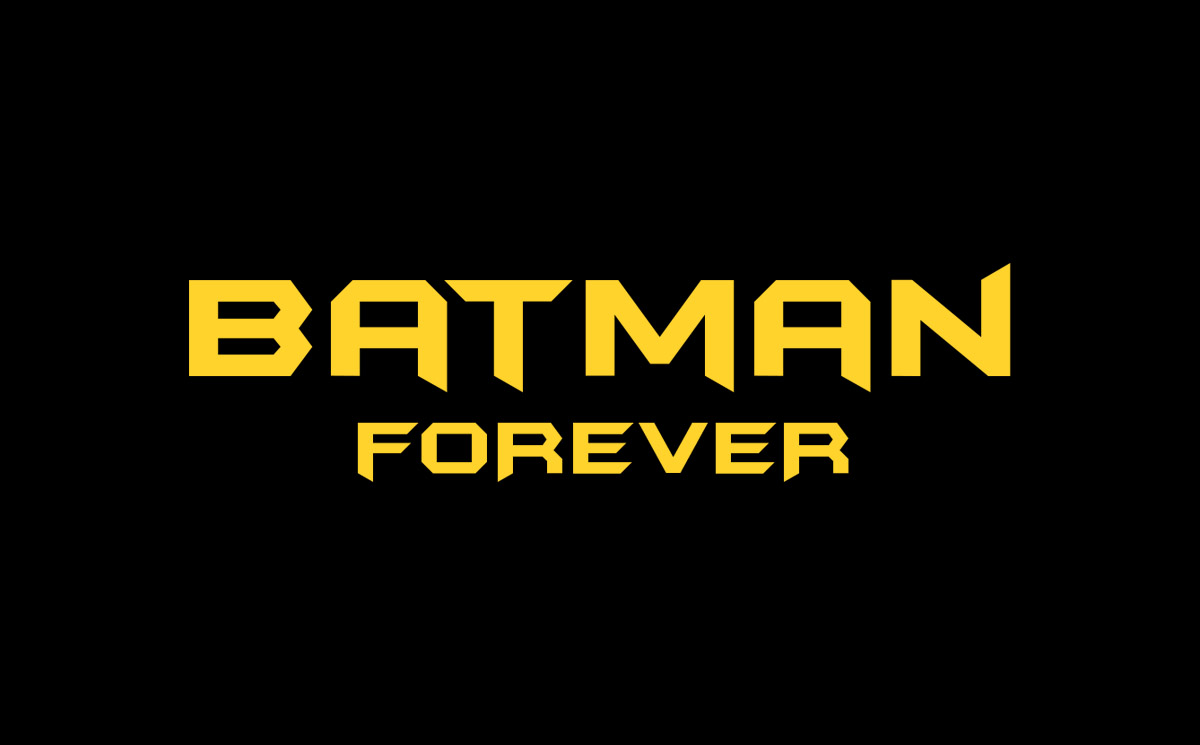
Nếu bạn đang tìm kiếm một bộ phông chữ mang phong cách mạnh mẽ, bứt phá và tràn đầy năng lượng cho các dự án sáng tạo, thì font thể thao cứng cáp Việt hóa SVN Batman chính là sự lựa chọn hoàn hảo không thể bỏ qua. Với cấu trúc nét chữ dày dặn, các góc vát dứt khoát cùng tinh thần hiện đại, bộ font này giúp truyền tải trọn vẹn sự quyết đoán và bản lĩnh trong từng thông điệp. Sự xuất hiện của bản Việt hóa chuẩn xác giúp các nhà thiết kế dễ dàng ứng dụng vào các sản phẩm đồ họa tiếng Việt mà không gặp bất kỳ trở ngại nào về mặt kỹ thuật.
Font Thể Thao Cứng Cáp Việt Hóa SVN Batman – Giải Pháp Typography Đột Phá Cho Thiết Kế Hiện Đại
Trong thế giới thiết kế đồ họa thương mại, typography đóng vai trò như chiếc chìa khóa định hình cảm xúc và truyền tải thông điệp cốt lõi của thương hiệu. Font thể thao cứng cáp Việt hóa SVN Batman nổi lên như một giải pháp thiết kế ấn tượng nhờ sự kết hợp hài hòa giữa hình khối hình học hiện đại và tinh thần thể thao cuồng nhiệt. Bộ font này không chỉ mang đến diện mạo mới mẻ cho các ấn phẩm quảng cáo mà còn khẳng định tính chuyên nghiệp trong từng chi tiết nhỏ nhất. Dù bạn đang thực hiện dự án truyền thông cho một giải đấu bóng đá lớn, thiết kế áo thi đấu cho đội tuyển esports hay xây dựng bộ nhận diện cho thương hiệu gym và fitness, SVN Batman đều có khả năng đáp ứng xuất sắc mọi yêu cầu khắt khe về thẩm mỹ lẫn công năng thị giác.
Phong cách thiết kế góc cạnh, đậm chất thể thao và tràn đầy uy lực
Font thể thao cứng cáp Việt hóa SVN Batman sở hữu những đường nét thẳng dứt khoát kết hợp cùng các góc vát tỉ mỉ, tạo nên cảm giác kiên cố và vô cùng hiện đại. Bộ chữ được xây dựng dựa trên tỷ lệ hình khối chuẩn xác, tạo ra sự cân bằng hoàn hảo giữa chiều rộng và chiều cao của từng ký tự. Nét chữ dày và đậm giúp các dòng tiêu đề (headline) luôn nổi bật, thu hút sự chú ý của người xem ngay từ cái nhìn đầu tiên. Tinh thần của font chữ này truyền tải sự quyết đoán, sức mạnh vượt trội và khát khao chiến thắng – những yếu tố vô cùng quan trọng đối với ngành công nghiệp thể thao và giải trí năng động.
Hỗ trợ Việt hóa toàn diện, chuẩn xác từng ký tự dấu tiếng Việt
Một trong những điểm cộng lớn nhất của font chữ này chính là phiên bản Việt hóa SVN được thực hiện một cách chỉn chu và tỉ mỉ. Các dấu thanh trong tiếng Việt như sắc, huyền, hỏi, ngã, nặng cùng các dấu phụ cho chữ cái ê, ô, ơ, ư, đ đã được thiết kế lại khéo léo để giữ nguyên tỉ lệ và phong cách góc cạnh của bộ chữ gốc. Nhờ đó, các bản thiết kế tiếng Việt của bạn sẽ không gặp phải tình trạng bị lỗi font, mất dấu hay các dấu thanh bị đè lên nét chữ. Việc hỗ trợ đầy đủ bộ gõ Unicode chuẩn giúp bạn dễ dàng soạn thảo văn bản trên mọi phần mềm mà vẫn đảm bảo tính thống nhất và tính thẩm mỹ cao nhất.
Tối ưu hóa cho thiết kế áo đấu, ấn phẩm Esports và Logo thương hiệu
Với đặc trưng nét chữ cứng cáp và vững chãi, SVN Batman đặc biệt phù hợp để ứng dụng trong thiết kế số áo và tên cầu thủ trên các bộ trang phục thi đấu như bóng đá, bóng rổ, bóng chuyền hay marathon. Nét chữ rõ ràng giúp khán giả dễ dàng nhận diện từ khoảng cách xa, đồng thời tạo nên vẻ ngoài ấn tượng và chuyên nghiệp cho đội hình thi đấu. Bên cạnh đó, font chữ này cũng là sự lựa chọn hàng đầu của các tổ chức Esports khi muốn thiết kế logo team, banner giải đấu, áo thi đấu hay poster sự kiện gaming. Bản chất góc cạnh của SVN Batman cực kỳ ăn khớp với phong cách futuristic (vị lai) và công nghệ cao của thế giới game hiện đại.
Gia tăng sức hút thị giác và tối ưu hóa hiệu quả truyền thông
Một thiết kế thành công không chỉ cần đẹp mà còn phải tạo ra sự chú ý và ghi dấu ấn mạnh mẽ trong lòng khách hàng. Font SVN Batman giúp bạn xây dựng một cấu trúc phân cấp thị giác (visual hierarchy) cực kỳ rõ ràng. Khi kết hợp kiểu chữ cứng cáp này cho phần tiêu đề chính cùng một font chữ nét mảnh, đơn giản cho phần nội dung chi tiết, bạn sẽ tạo ra sự tương phản thị giác vô cùng ấn tượng. Điều này không chỉ giúp thu hút ánh nhìn của khách hàng vào thông điệp quan trọng nhất mà còn làm tăng tính thẩm mỹ tổng thể, giúp chiến dịch truyền thông hay ấn phẩm quảng cáo của bạn đạt hiệu quả chuyển đổi tối đa.
Những Ứng Dụng Thực Tế Xuất Sắc Của Font Thể Thao Việt Hóa SVN Batman
Nhờ tính linh hoạt và phong cách thiết kế đặc trưng, font thể thao cứng cáp Việt hóa SVN Batman có thể được áp dụng rộng rãi trong nhiều lĩnh vực sáng tạo khác nhau. Dưới đây là những gợi ý ứng dụng thực tế giúp bạn khai phá tối đa tiềm năng của bộ font này:</p>
- Thiết kế ấn phẩm truyền thông thể thao: Làm banner, poster quảng cáo cho các giải đấu bóng đá, thể hình, marathon, võ thuật đối kháng MMA hay các sự kiện thể thao học đường.
- Nhận diện thương hiệu Fitness & Gym: Thiết kế logo, slogan, biển hiệu cho các trung tâm thể hình, thương hiệu quần áo thể thao, phụ kiện tập luyện chuyên nghiệp.
- Thiết kế bao bì sản phẩm cá tính: Áp dụng cho các sản phẩm thực phẩm bổ sung, sữa tăng cơ, nước uống vận động, dụng cụ tập thể thao mang phong cách mạnh mẽ.
- Ấn phẩm sự kiện và giải trí: Tạo tiêu đề cho poster phim hành động, thumbnail video YouTube chuyên về game, bìa album nhạc Rock, Hip-hop hoặc các banner sự kiện âm nhạc sôi động.